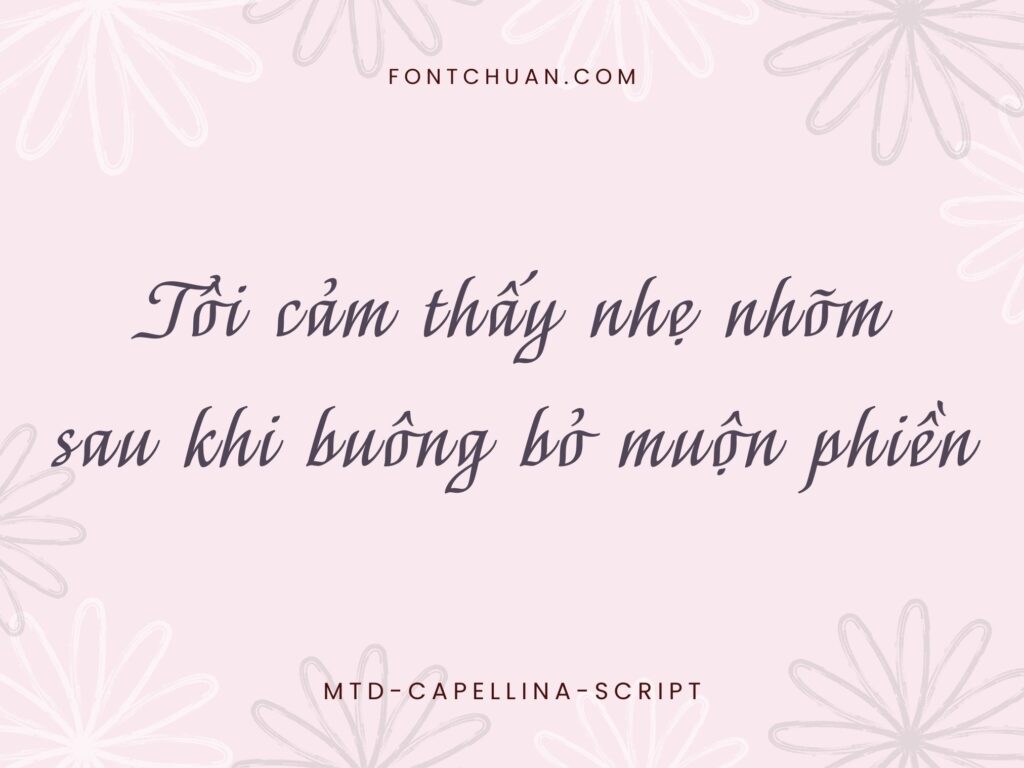
Font MTD Capellina Script Việt Hóa
Font MTD Capellina Script là một kiểu chữ viết tay trang nhã, được thiết kế bởi Ricardo Esteves Gomes từ Outras Fontes và đã được Việt hóa bởi Mộc Hạ. Font này hỗ trợ đầy đủ tiếng Việt cùng hơn 90 ngôn ngữ khác, mở rộng khả năng ứng dụng trong các thiết kế đa ngôn ngữ. Đây là một trong những phông chữ được cộng đồng thiết kế đánh giá cao và sử dụng trong nhiều dự án sáng tạo, đáp ứng nhu cầu đa dạng của người dùng.
MTD Capellina Script nổi bật với các đường nét mềm mại và uyển chuyển, tạo cảm giác thân thiện và gần gũi. Font rất phù hợp cho các thiết kế logo, tiêu đề, bao bì sản phẩm, thiệp mời và các ấn phẩm đòi hỏi sự tinh tế và nghệ thuật. Các ngành nghề phù hợp bao gồm quảng cáo, giáo dục, công nghệ, thiệp cưới và ảnh cưới. Font này cũng lý tưởng cho các sự kiện như Tết, Giáng sinh, Valentine và các lễ hội khác.